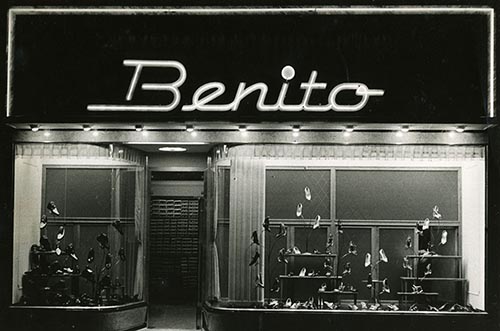
Calzados Benito (Años 60)
Calzados Benito inició su andadura en 1938. Una tienda ya integrada en las calles de la ciudad, hoy en día está en la Calle Juán de Herrera, junto al Ayuntamiento.
El rótulo que aquí se reproduce, no es el que está actualmente en la tienda. Es de los años 60, y ya aparece en el magnífico libro de César Pombo «Vamos de tiendas» (2015), siendo a nuestro criterio uno de esos que son únicos por su tipografía y por el efecto visual que hacía el neón. La «E» del póster del Abecedario de Santander, está sacada de este rótulo 😉